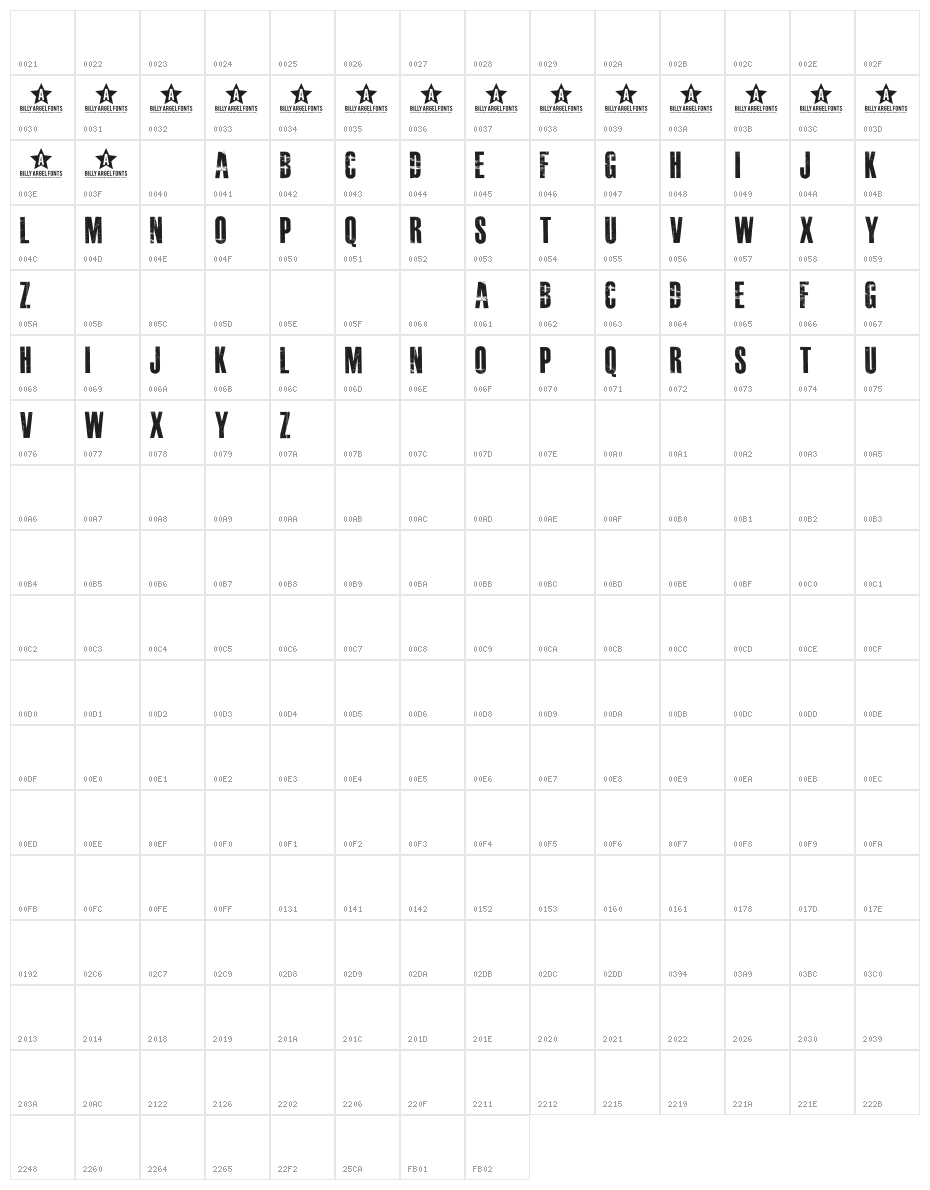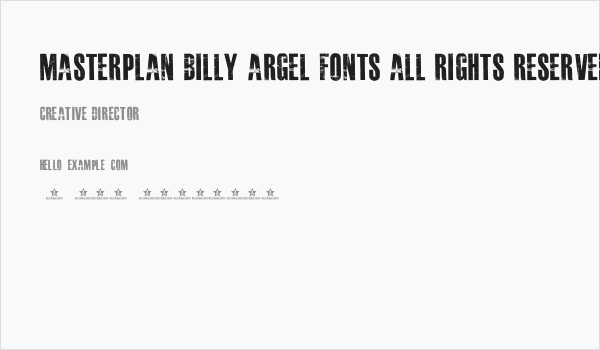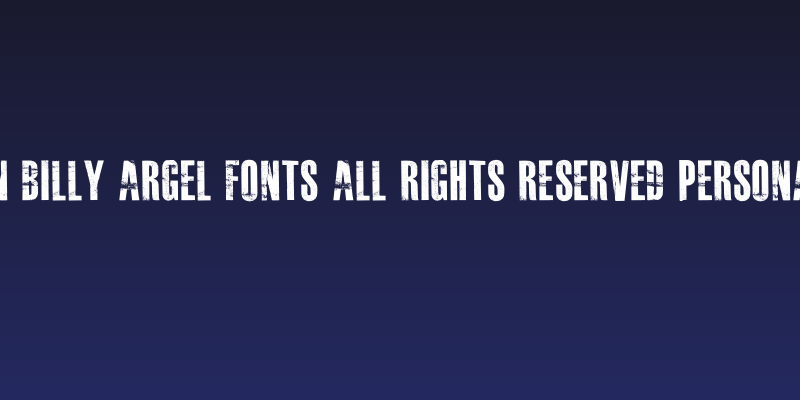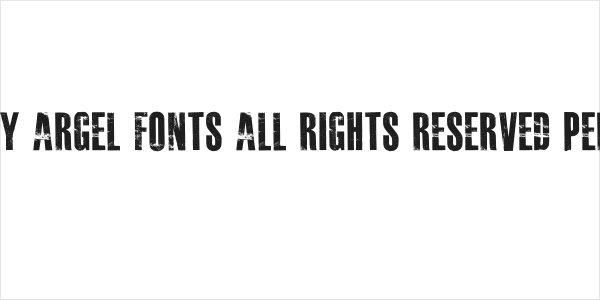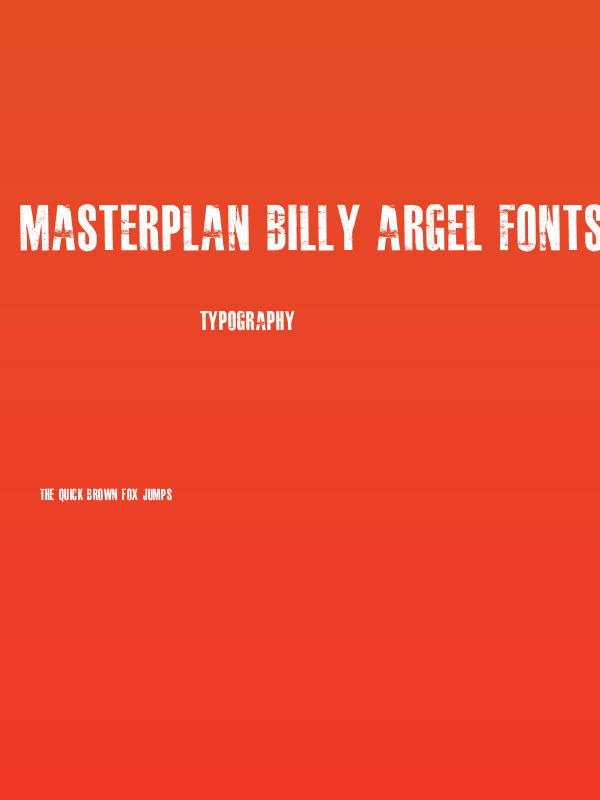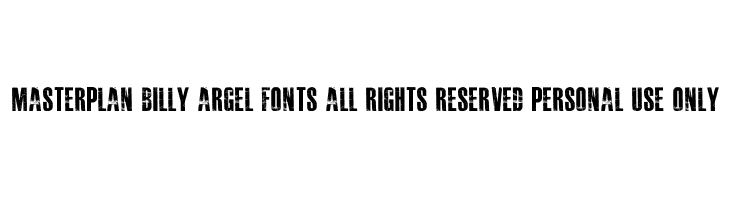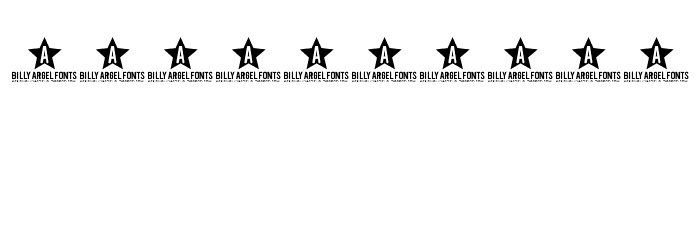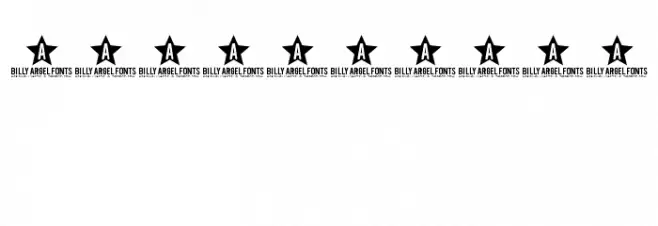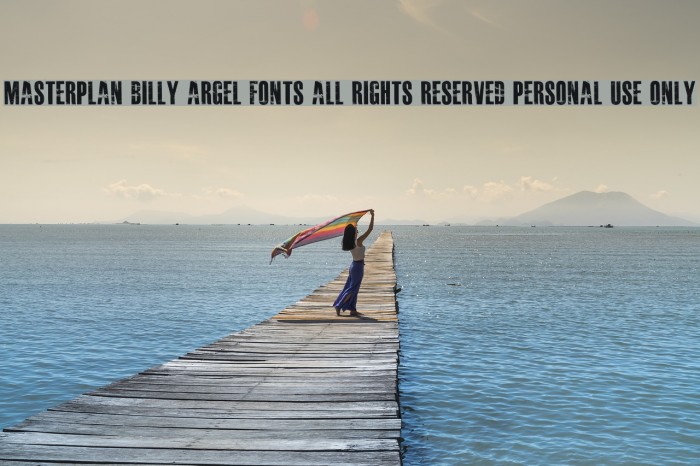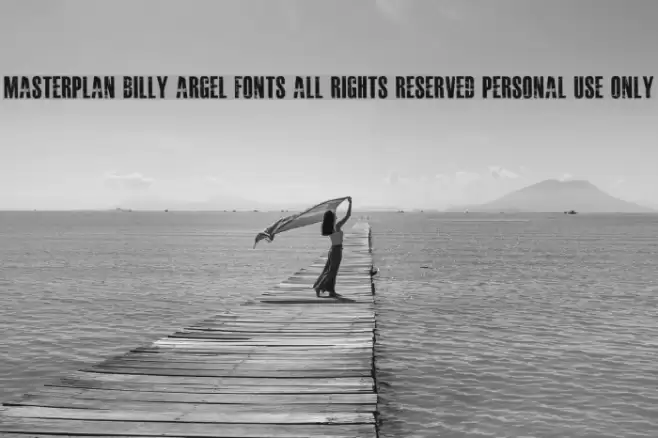
MASTERPLAN Billy Argel fonts All Rights Reserved personal use only Font
✎ Messy
| Projets proposés | Ideal for posters, album covers, branding, and any design requiring a bold, vintage aesthetic. |